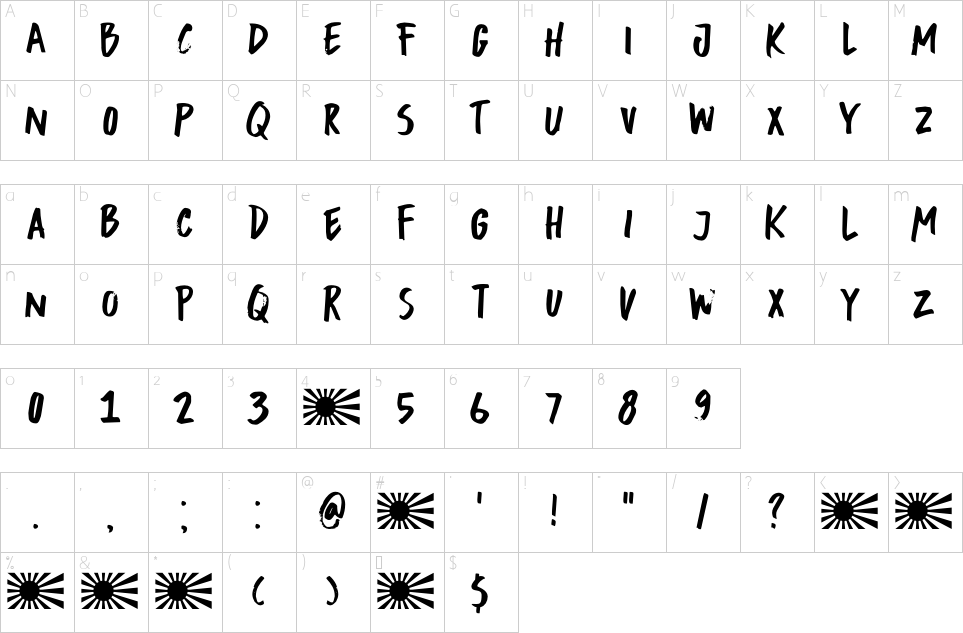
DK Buntaro Font
A fonte DK Buntaro é uma opção para designers que buscam uma tipografia versátil e elegante. Desenvolvida por Hanoded, esta fonte foi projetada para oferecer um toque único e moderno à sua obra de arte digital. Com um design cuidadosamente elaborado, a DK Buntaro pode ser usada tanto em aplicações Windows quanto Mac, tornando-se uma fonte versátil que cabe às necessidades de qualquer designer. Esta font foi descarregada mais de 9000 vezes, o que comprova seu valor e popularidade entre os designers digitais. Seja para criar um design editorial, artesanato digital ou simplesmente decorar seus documentos em formato digital, a DK Buntaro oferece uma solução acessível e eficaz para qualquer designer em busca de uma fonte única e versátil.
Mapa de caracteres da fonte DK Buntaro Font